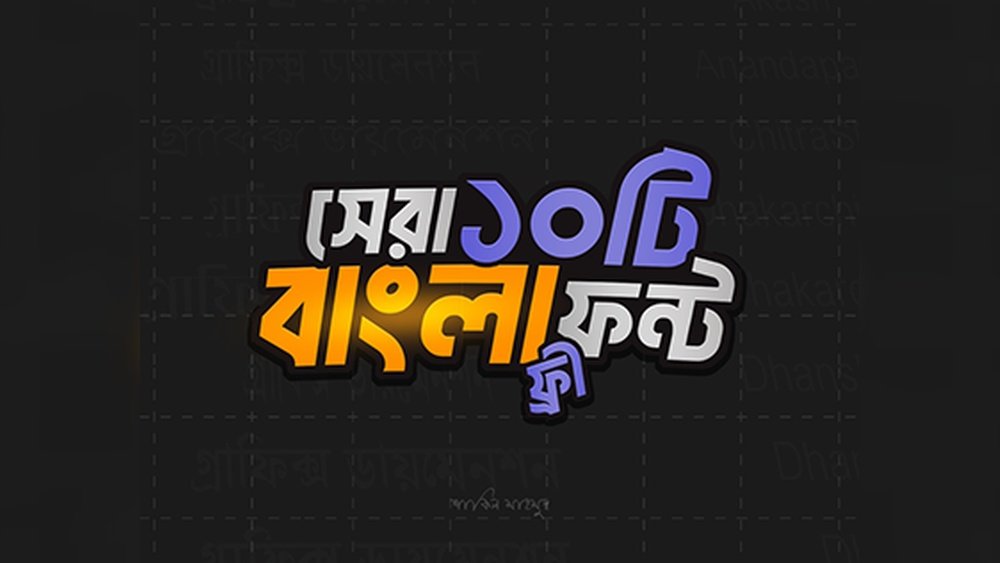
আপনি কি ভিডিও এডিটিংয়ে বাংলা ফন্ট নিয়ে কাজ করছেন? ভিডিওর মেসেজ যতই শক্তিশালী হোক না কেন, যদি ফন্ট সুন্দর এবং স্পষ্ট না হয়, দর্শকের মনোযোগ হারানো সহজ। তাই আপনার ভিডিওর জন্য সেরা বাংলা ফন্ট বেছে নেওয়া খুবই গুরুত্বপূর্ণ। এই লেখায় আপনি জানতে পারবেন এমন কিছু বাংলা ফন্টের কথা, যা আপনার ভিডিওকে করবে আরও প্রফেশনাল এবং চোখে পড়ার মতো। নিজের কাজকে আরও উন্নত করতে এবং দর্শকের মন জয় করতে চান?
তাহলে পুরো লেখাটি পড়ুন, কারণ আমরা নিয়ে এসেছি আপনার জন্য বেস্ট বাংলা ফন্টের এক্সপার্ট গাইড।
বাংলা ফন্টের গুরুত্ব
ভিডিও এডিটিংয়ে বাংলা ফন্টের গুরুত্ব অপরিসীম। ফন্ট শুধু লেখা নয়, এটি একটি বার্তা বহন করে। সঠিক ফন্ট ভিডিওর মেজাজ ও বার্তা স্পষ্ট করে তোলে।
ভালো ফন্ট ব্যবহার করলে ভিডিওর প্রভাব অনেক বেড়ে যায়। দর্শক সহজে তথ্য বুঝতে পারে। তাই বাংলা ফন্ট নির্বাচন খুবই গুরুত্বপূর্ণ।
ভিডিওতে ফন্টের প্রভাব
ভিডিওতে ফন্ট দর্শকের মনোযোগ আকর্ষণ করে। ফন্টের আকার, স্টাইল এবং স্পেসিং ভিডিওর পেশাদারিত্ব বাড়ায়। ভালো ফন্ট ভিডিওর বার্তা সহজে পৌঁছে দেয়। ভুল ফন্ট ব্যবহার করলে ভিডিও অস্পষ্ট ও অব্যবস্থাপিত লাগে।
ভিজ্যুয়াল কমিউনিকেশনে ফন্টের ভূমিকা
ফন্ট ভিজ্যুয়াল কমিউনিকেশনের একটি গুরুত্বপূর্ণ অংশ। এটি ভাষার সঙ্গে অনুভূতি ও ভাব প্রকাশ করে। সঠিক ফন্ট দর্শকের সাথে সংযোগ গড়ে তোলে। তাই ভিডিও তৈরিতে ফন্টের গুরুত্ব অনেক বেশি।
সেরা বাংলা ফন্টের বৈশিষ্ট্য
ভালো বাংলা ফন্ট বেছে নেওয়া মানে ভিডিও সম্পাদনার মান বাড়ানো। সেরা বাংলা ফন্টের কিছু বিশেষ বৈশিষ্ট্য থাকে। এই বৈশিষ্ট্যগুলো ভিডিওর টেক্সটকে সহজে পড়ার মতো এবং সুন্দর করে তোলে।
একটি ফন্ট ভালো হলে তা ভিডিওর বার্তাকে স্পষ্টভাবে প্রকাশ করে। তাই পঠনযোগ্যতা, ডিজাইন এবং বিভিন্ন প্ল্যাটফর্মে কাজ করার ক্ষমতা জরুরি।
পঠনযোগ্যতা ও স্পষ্টতা
পঠনযোগ্যতা ভালো মানে দর্শক সহজে টেক্সট পড়তে পারে। বাংলা ফন্টে অক্ষরগুলো স্পষ্ট হওয়া উচিত। ছোট আকারেও ফন্টটি ঝাপসা বা অস্পষ্ট না হওয়া জরুরি। ভিডিওর স্ক্রিনে টেক্সট যত সহজে পড়া যাবে, তত বেশি মানুষের মনোযোগ থাকবে।
আকর্ষণীয় ডিজাইন
বাংলা ফন্টের ডিজাইন সুন্দর এবং আকর্ষণীয় হওয়া দরকার। ভিডিওর থিম এবং বিষয়ের সঙ্গে মানানসই ফন্ট বেছে নিতে হবে। ফন্টের স্টাইল যেন ভিডিওর মেজাজকে আরো ভালোভাবে তুলে ধরে। খুব বেশি জটিল ডিজাইন দর্শকের মনোযোগ হারাতে পারে।
বিভিন্ন প্ল্যাটফর্মে সামঞ্জস্য
ভিন্ন ধরণের ভিডিও এডিটিং সফটওয়্যার এবং প্ল্যাটফর্মে ফন্টের কাজ করা জরুরি। ফন্টটি যেন সব প্ল্যাটফর্মে ঠিকঠাক দেখা যায় এবং কোনো সমস্যা না হয়। এতে ভিডিও তৈরির সময় ফন্ট নিয়ে ঝামেলা কম হয়।
জনপ্রিয় বাংলা ফন্টসমূহ
ভিডিও এডিটিংয়ে বাংলা ফন্টের গুরুত্ব অপরিসীম। ভালো ফন্ট ভিডিওর বার্তা স্পষ্ট করে তোলে। জনপ্রিয় বাংলা ফন্টগুলো ব্যবহার করে কাজের মান বাড়ানো যায়। নিচে কিছু জনপ্রিয় বাংলা ফন্টের পরিচয় দেওয়া হলো।
নোটো সান্স বাংলা
নোটো সান্স বাংলা একটি আধুনিক এবং পরিষ্কার ফন্ট। এটি গুগলের তৈরি। এই ফন্টটি অনেক ভিডিও এডিটরে ব্যবহারযোগ্য। সহজে পড়া যায় এবং সব ধরণের স্ক্রিনে ভালো দেখা যায়।
কালপুরুষ
কালপুরুষ ফন্টটি ঐতিহ্যবাহী বাংলা অক্ষরধারা অনুসরণ করে তৈরি। এটি ভিডিওতে শৈল্পিক ছোঁয়া যোগ করে। বিশেষ করে নাটক বা সাহিত্যভিত্তিক ভিডিওতে কালপুরুষ ফন্ট বেশ জনপ্রিয়।
সিয়াম রুপালি
সিয়াম রুপালি একটি মসৃণ ও নরম ফন্ট। এটি চোখে আরামদায়ক লাগে। ভিডিওর টেক্সটে প্রফেশনাল লুক আনার জন্য এই ফন্টটি ভালো বিকল্প। বিভিন্ন ধরনের প্রকল্পে এটি ব্যবহার করা যায়।
অ্যাডোবি বাংলা
অ্যাডোবি বাংলা ফন্টটি অ্যাডোবির অফিসিয়াল ফন্ট। এটি অনেক ভিডিও এডিটিং সফটওয়্যারে সমর্থিত। ফন্টের গঠন সুন্দর এবং স্পষ্ট। ভিডিওর জন্য এটি একটি শক্তিশালী পছন্দ।
ভিডিও এডিটিংয়ের জন্য ফন্ট বাছাই
ভিডিও এডিটিংয়ে সঠিক ফন্ট বাছাই করা খুবই গুরুত্বপূর্ণ। এটি ভিডিওর মান ও দর্শকের আগ্রহ বৃদ্ধি করে। ফন্টের মাধ্যমে ভিডিওর বার্তা স্পষ্ট ও আকর্ষণীয় হয়। তাই ফন্ট নির্বাচন সময় মনোযোগ দিতে হয়।
ভিন্ন ধরনের ভিডিওর জন্য ফন্টের ধরন আলাদা হতে পারে। থাম্বনেইল ও সাবটাইটেলেও ফন্টের গুরুত্ব অপরিসীম। ফন্টের সাইজ ও রঙ ঠিক না হলে ভিডিওর প্রভাব কমে যায়।
ভিডিওর ধরন অনুযায়ী ফন্ট নির্বাচন
প্রেজেন্টেশন ভিডিওতে পরিষ্কার ও সহজবোধ্য ফন্ট বেছে নিন।
ব্লগ বা তথ্যভিত্তিক ভিডিওতে পঠনযোগ্য ফন্ট বেশি উপযোগী।
বিনোদনমূলক ভিডিওতে একটু সৃজনশীল ও আকর্ষণীয় ফন্ট ব্যবহার করুন।
ভিডিওর মেজাজ ও থিমের সাথে ফন্টের মিল থাকা জরুরি।
থাম্বনেইল ও সাবটাইটেল ফন্ট
থাম্বনেইলে বড় ও চোখে পড়ার মতো ফন্ট দরকার।
ফন্ট সাইজ ও রঙের গুরুত্ব
ছোট ফন্ট দর্শকের জন্য পড়া কঠিন করে তোলে।
রঙ ঠিক না হলে ফন্ট পটভূমির সাথে মিশে যেতে পারে।
উজ্জ্বল ও পরিপাটি রঙ ব্যবহার করলে দর্শক আকৃষ্ট হয়।
Conclusion
ভিডিও এডিটিংয়ের জন্য সঠিক বাংলা ফন্ট বেছে নেওয়া কাজের গুণগত মান বাড়ায়। ফন্টের স্পষ্টতা এবং পড়ার সুবিধা ভিডিওর প্রভাব বৃদ্ধি করে। সহজ এবং সুন্দর ফন্ট ব্যবহার করলে দর্শকদের মনোযোগ ধরে রাখা সহজ হয়। বিভিন্ন ফন্ট ট্রাই করে নিজস্ব স্টাইল খুঁজে পাওয়া উচিত। এর ফলে ভিডিও আরও প্রফেশনাল এবং আকর্ষণীয় হয়। তাই, ভালো ফন্ট নির্বাচন ভিডিও এডিটিংয়ের গুরুত্বপূর্ণ অংশ।